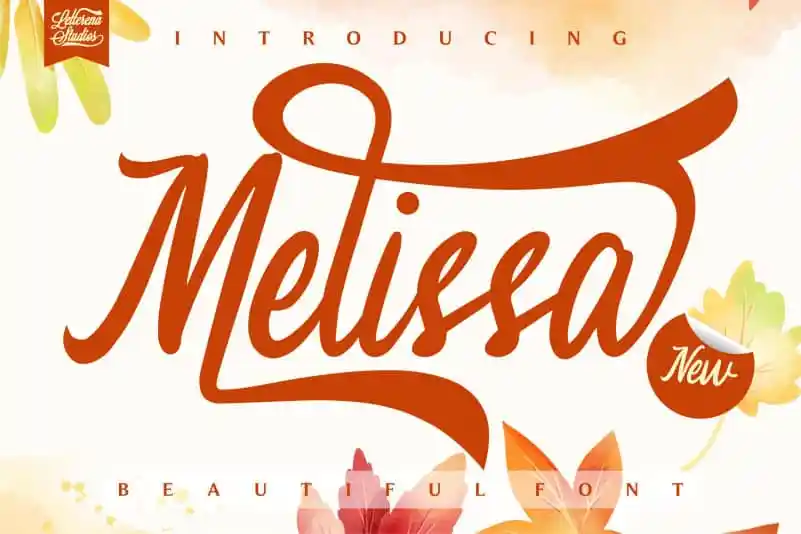
Melissa Script Font – Download Grátis
A Melissa Script Font é uma fonte de escrita à mão com personalidade forte, criada sob a influência de uma bela varinha mágica. Suas linhas suaves e detalhes finos tornam-na perfeita para quem busca um estilo elegante em seu trabalho diário ou profissional, seja ele criar cartões postais artesanais, projetar conteúdo digital, elaborar apresentações empresariais ou criar lindas cartas de cumprimento. Esta fonte ao vivo é uma escolha ideal para quem valoriza a personalização e o toque criativo em seus projetos gráficos. Com ela, você pode transformar qualquer projeto em algo verdadeiramente único e imprimível. Não perca esta oportunidade de adicionar um toque autêntico à sua designografia com Melissa Script Font.